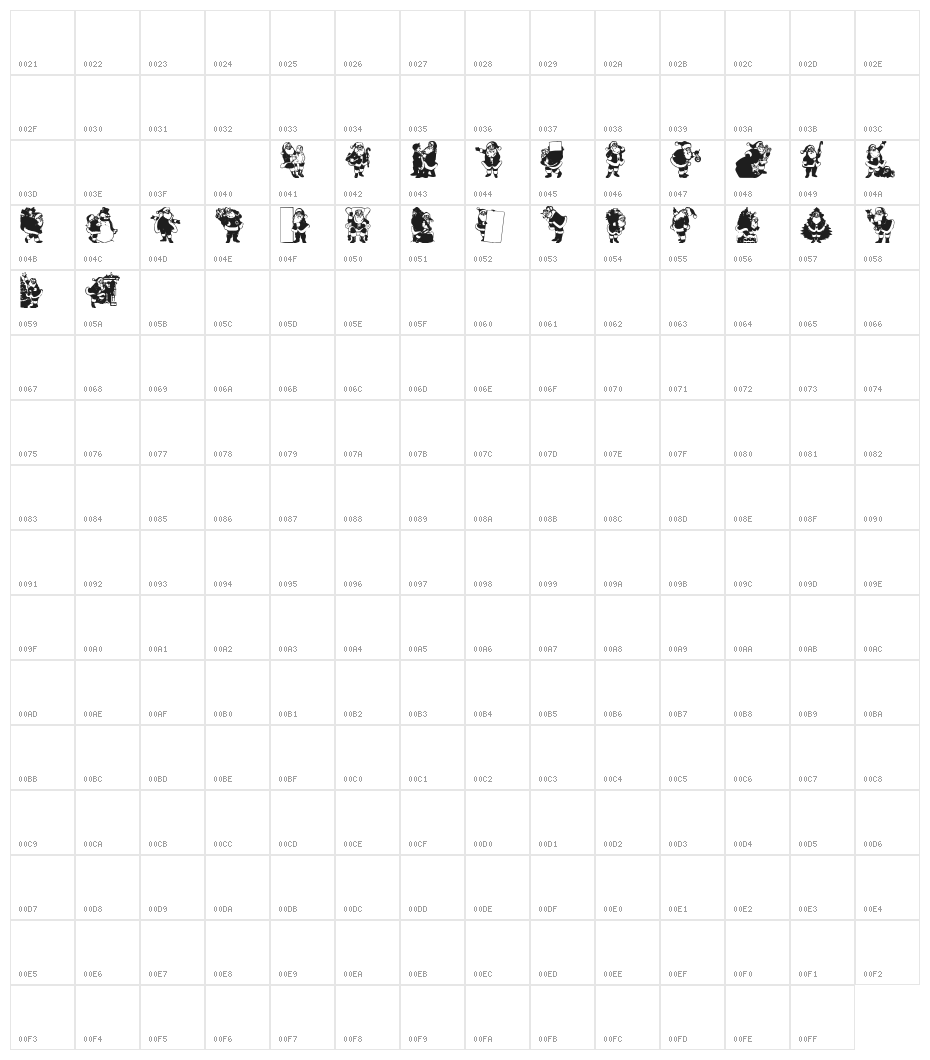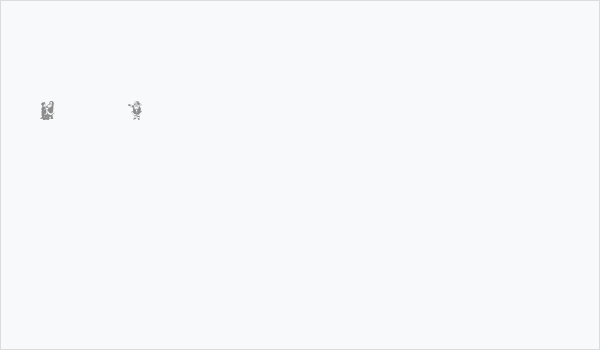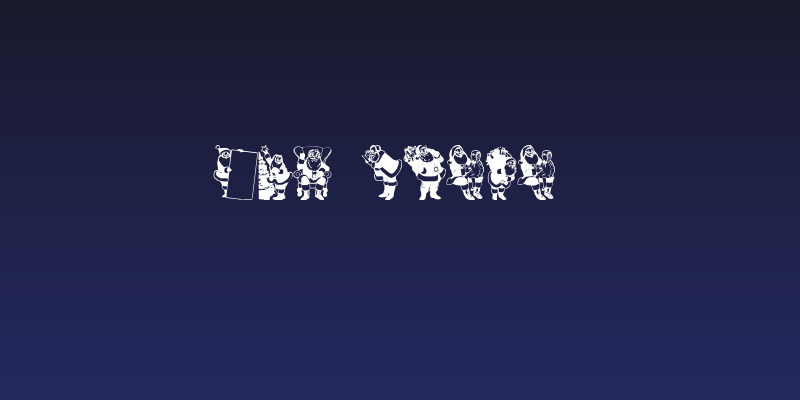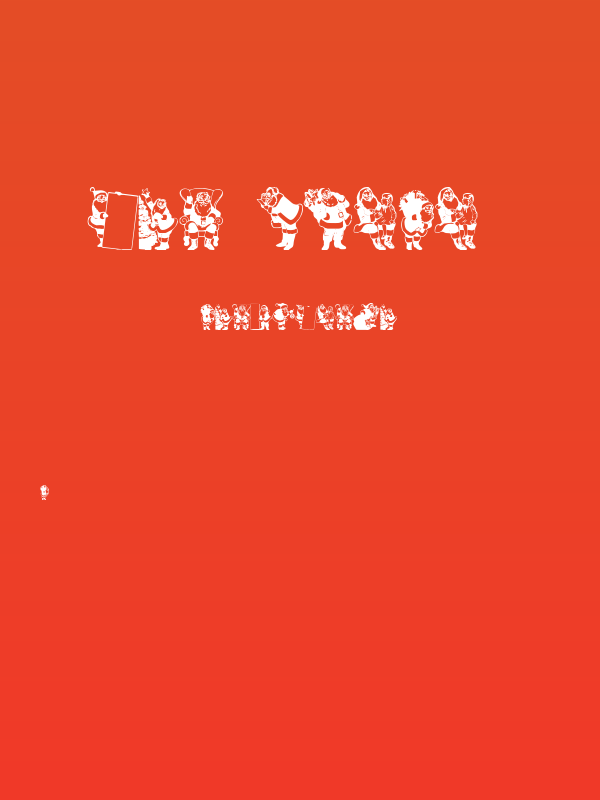
ryp_snata1 Font
✎ Christmas (Xmas)
| Gesamtstil | Playful, Festive, Decorative |
| Anwendungsfall | Headlines, Logos, Posters, Themed graphics |
| Vorgeschlagene Projekte | Holiday greeting cards, Christmas party invitations, festive posters, children’s event materials, seasonal branding. |